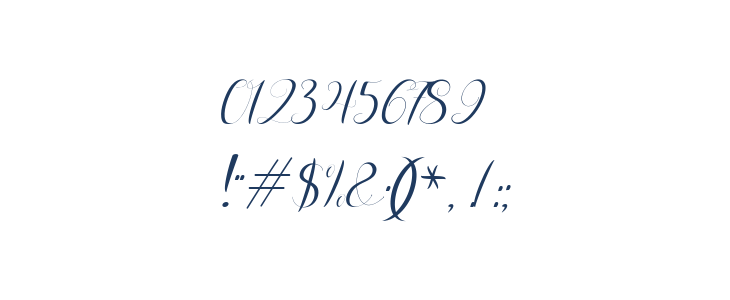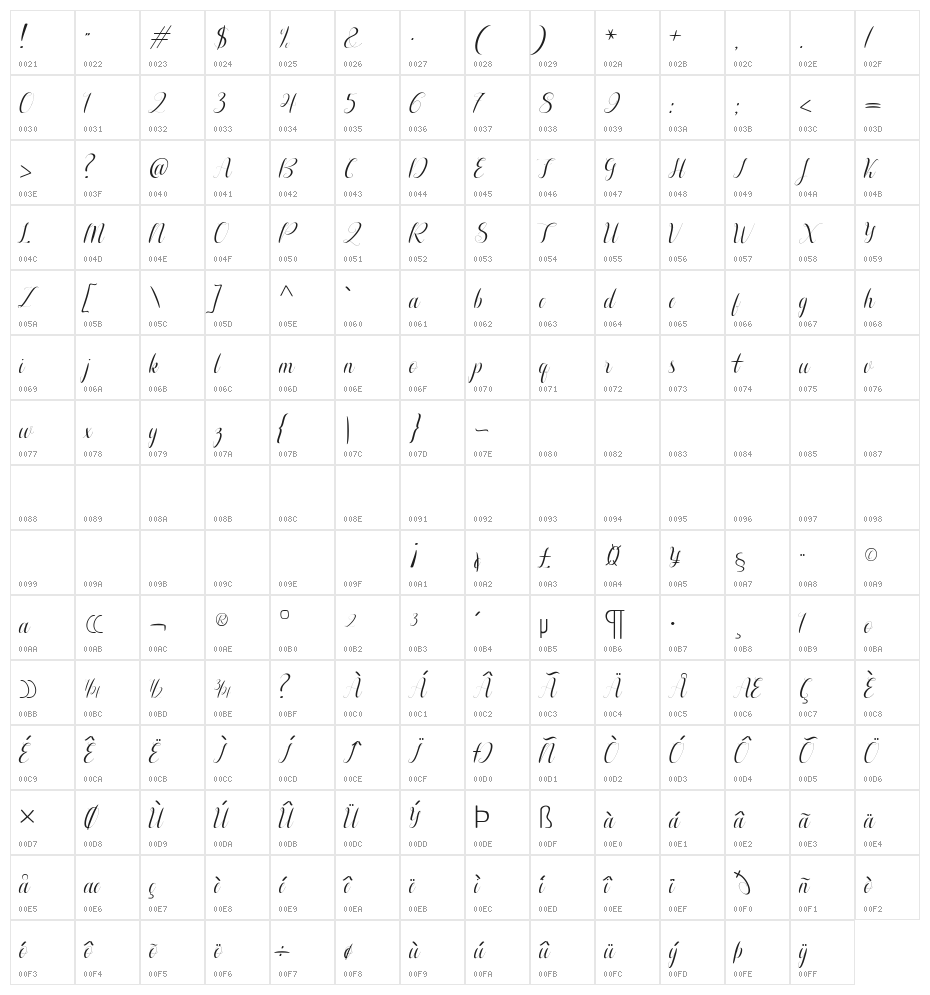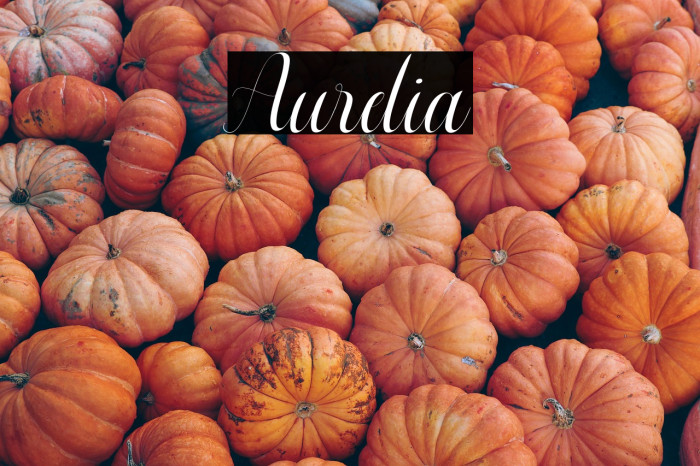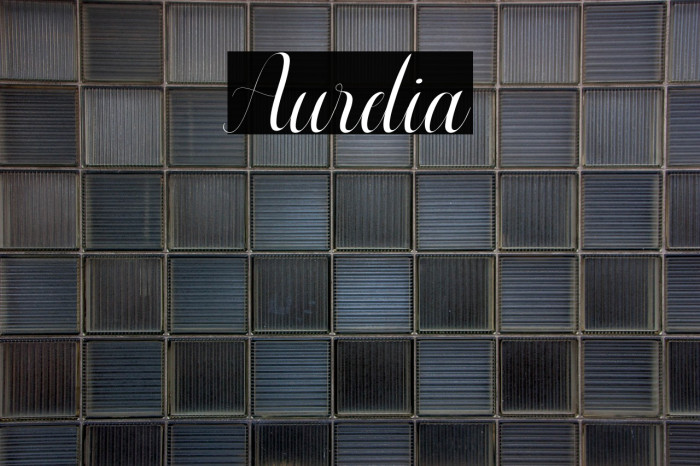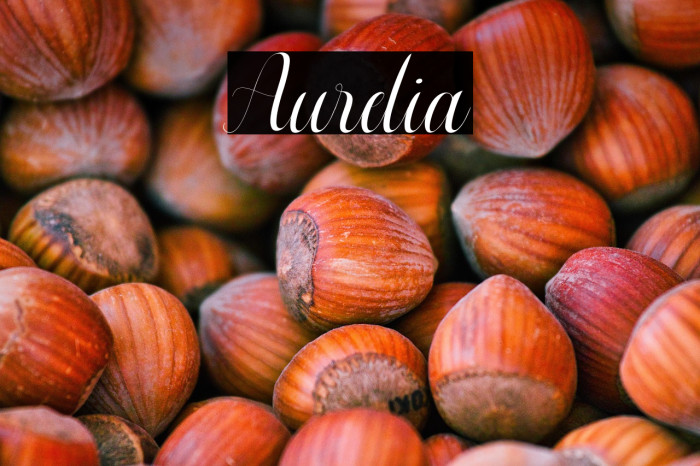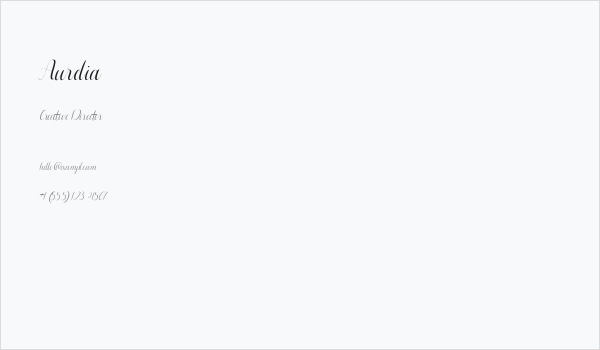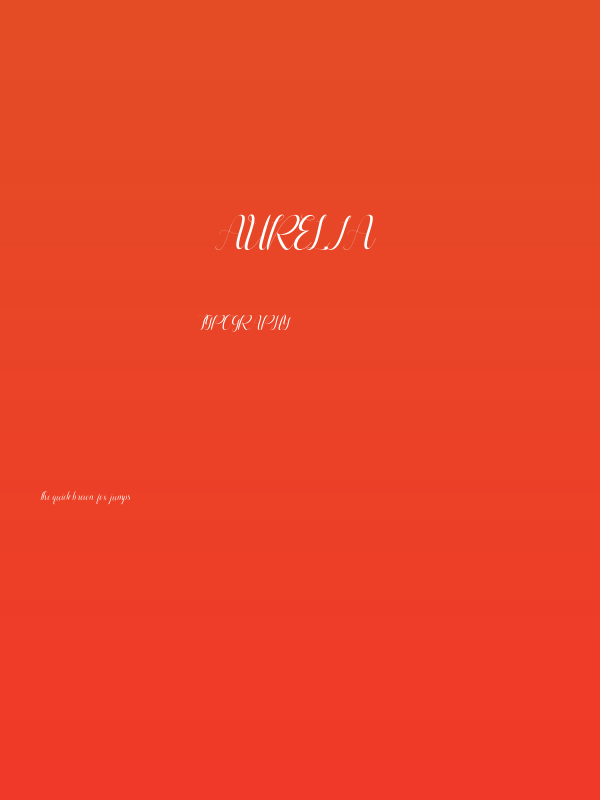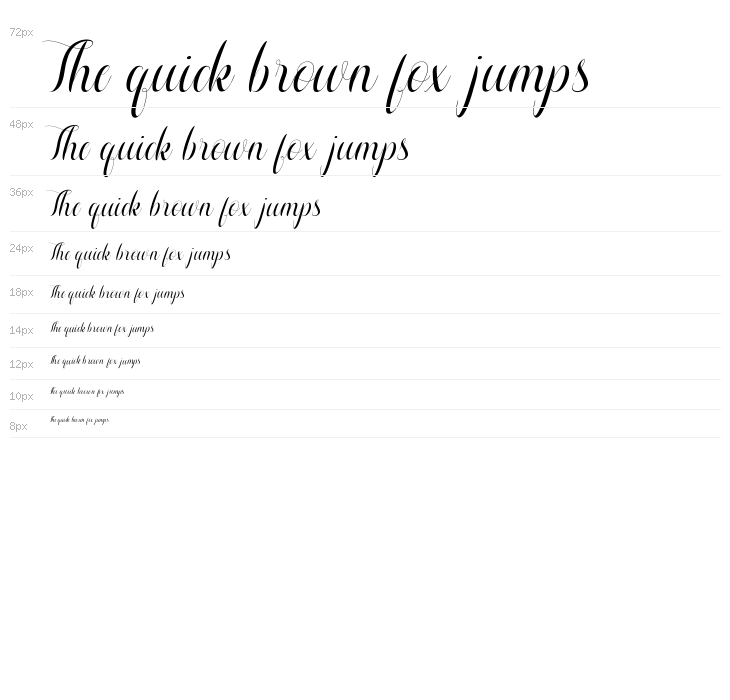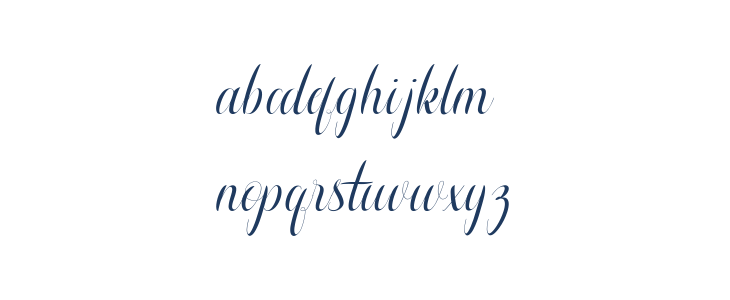
Aurelia Font
| Gesamtstil | Elegant, Artistic |
| Anwendungsfall | Logos, Invitations, Branding |
| Vorgeschlagene Projekte | Ideal for wedding invitations, luxury branding, elegant packaging, and high-end editorial design. |